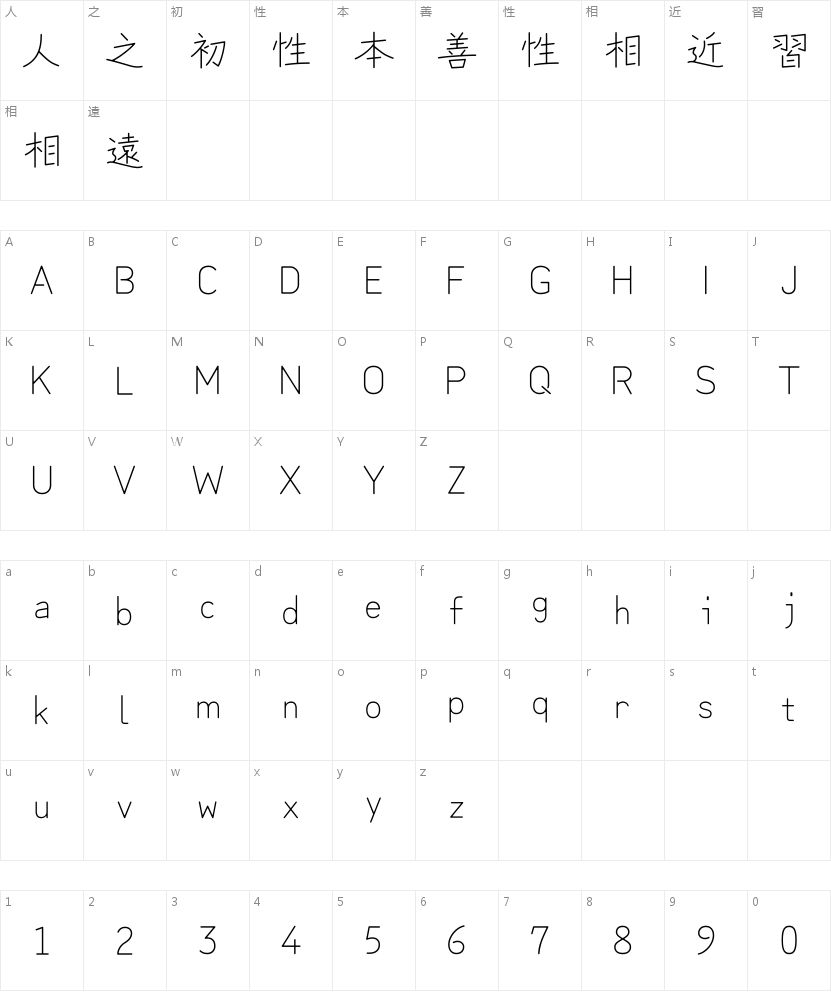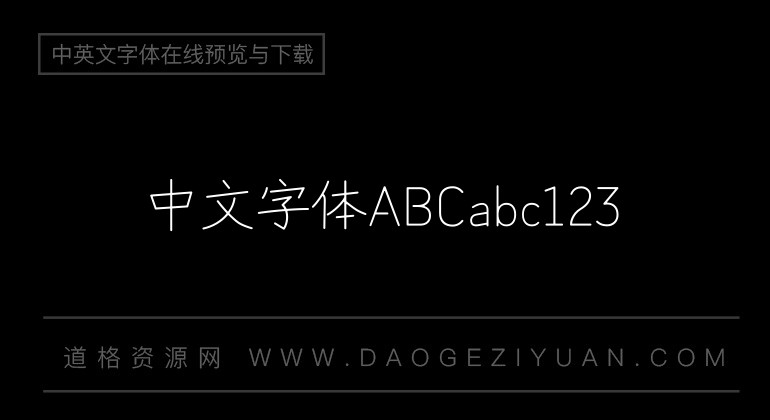
苦累蛙圆体-CJK-TC Light
苦累蛙圆体CJK-TC Light是一种中文字体,它是由设计师酷德所创建的。该字体是基于圆形设计的,并具有清晰易读的特点。它适用于各种场合,如文本、标题、海报、标志等。此字体的轮廓清晰,线条平滑。它有三种字重:Light、Regular和Bold,适用于不同的设计需求。另外,该字体还包括繁体中文和简体中文,可以满足不同语言的需要。
苦累蛙圆体-CJK-TC Light是一款非常不错的手写艺术字体,具有很好的视觉感,适合于文化类的宣传设计、商业类品牌的广告和产品包装设计以及个性化文字排版等较多场景。